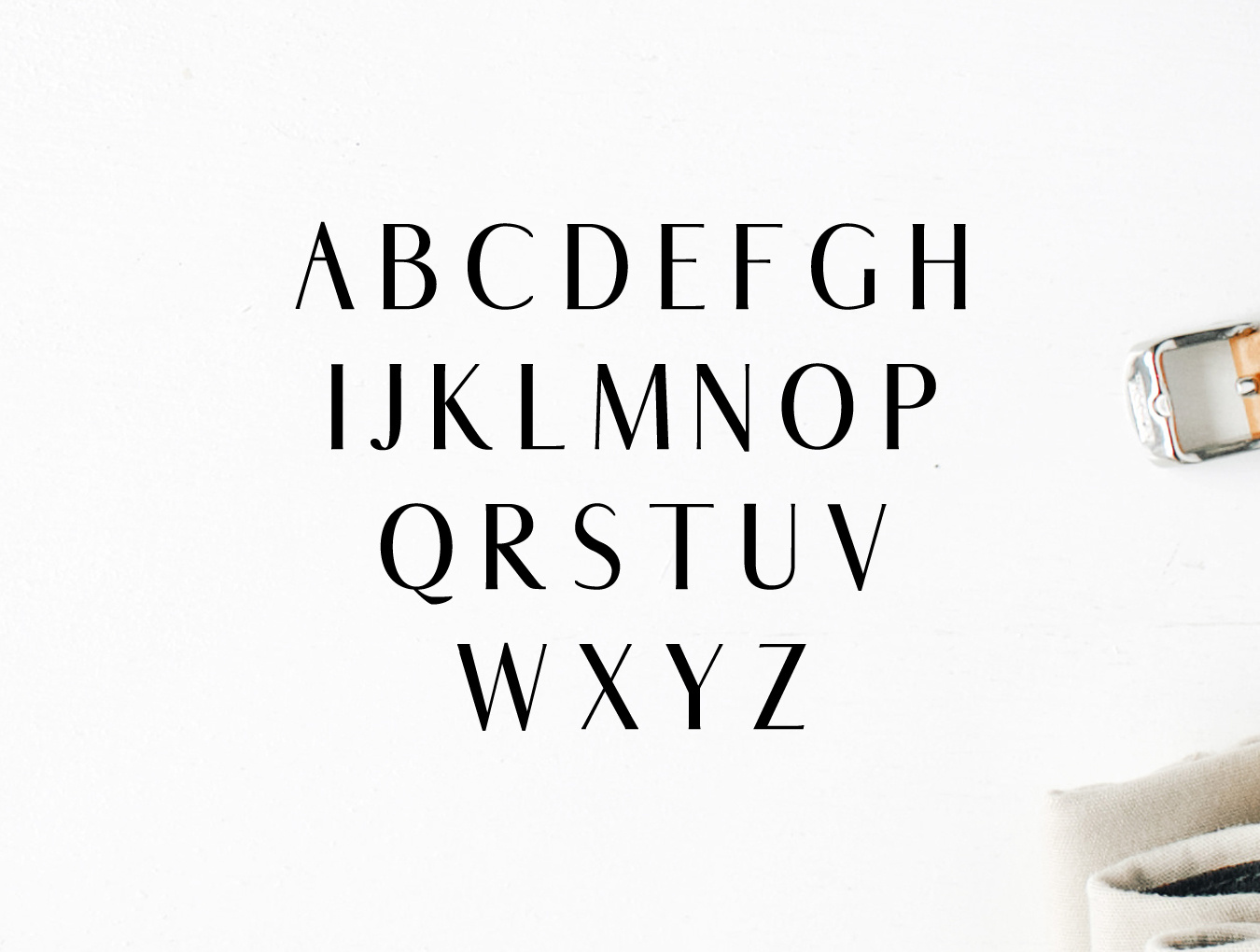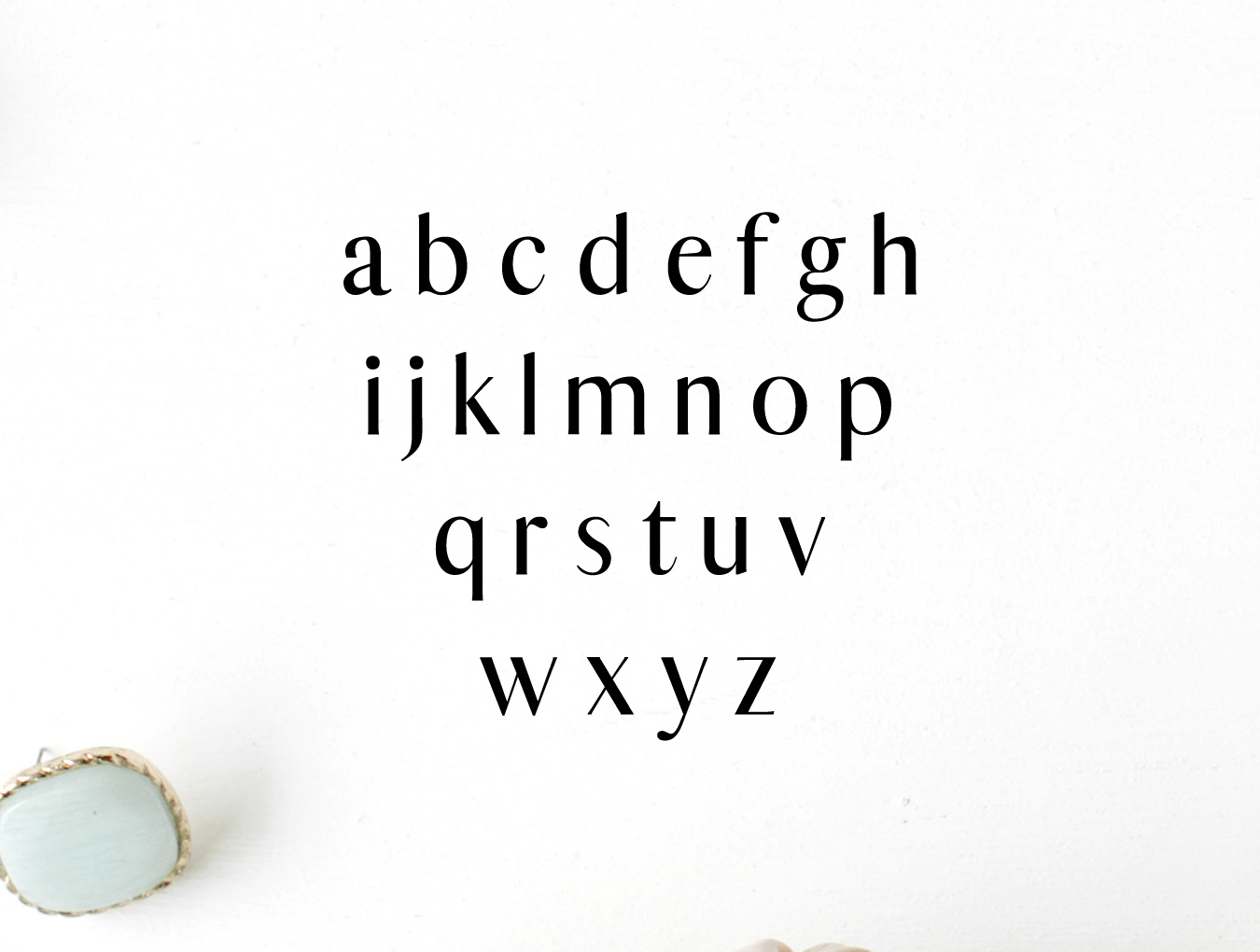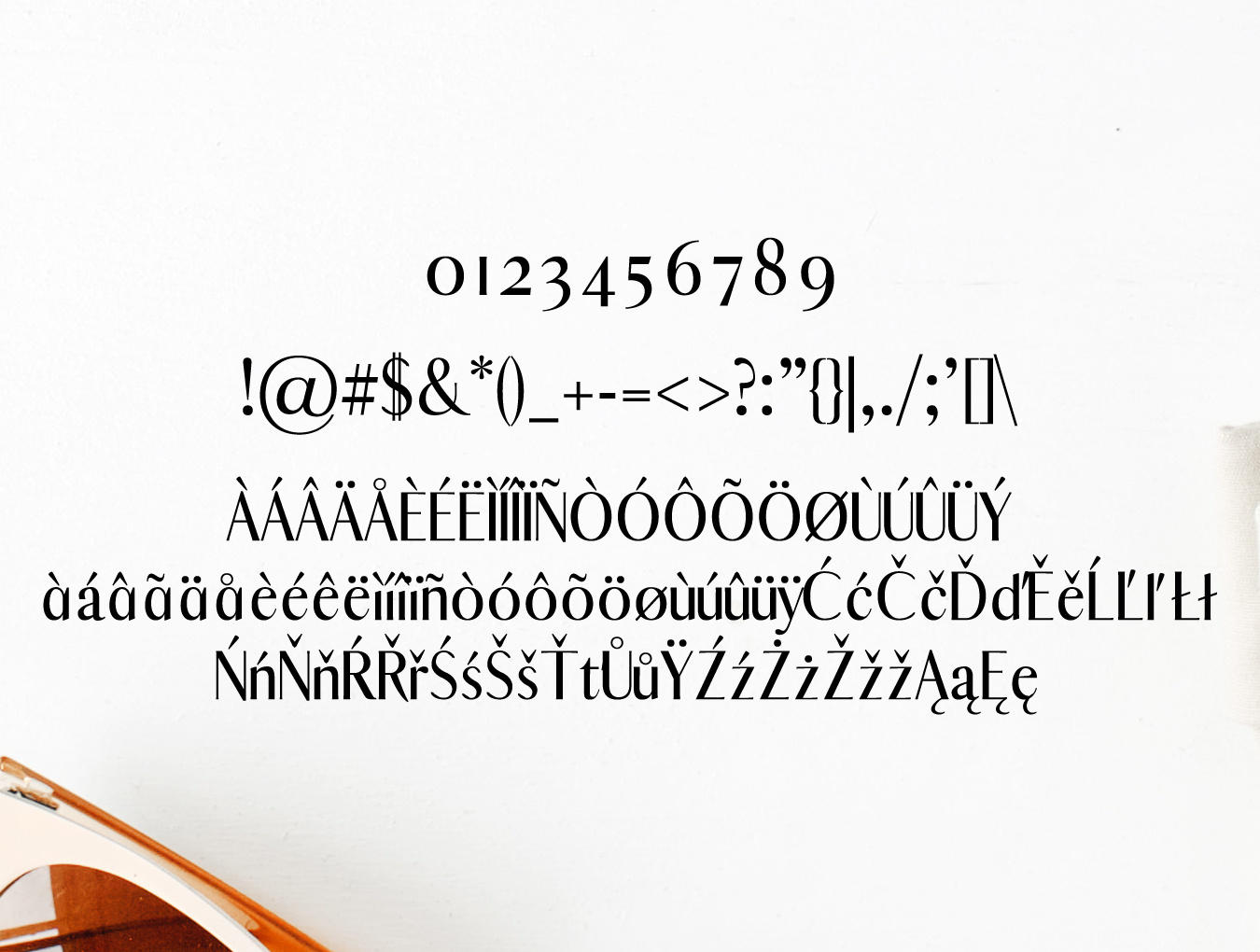
Abiah Sans Serif 5字体家庭装,Abiah Sans Serif字体
Abiah Sans Serif 5 Font Family Pack, Abiah Sans Serif Typeface
Abiah Sans Serif字体是一种最小的无衬线字体,包含5个重量,它具有独特和现代的无衬线外观和感觉。非常适合华丽的徽标,标题,网页布局和品牌。如果你想尝试一个优雅的外观,它看起来华丽,所有帽子都有宽大的间距,或者在大写字母和小写字母中完美无瑕。